月刊MdN 2018年11月号(特集:明朝体を味わう。/付録小冊子 書体見本帳)
夜な夜な、「早く明朝体ソムリエになりたーい」と叫ぶ明朝体人間は必読か、MdN編集部編集による2018年10月6日に発売された「月刊MdN」2018年11月号では、2018年11月号では、「明朝体を味わう。明朝体ソムリエになりたい」と題して、明朝体の成り立ちや味わいを解説する特集が掲載されている。
また特集として連動した特別付録「明朝体テイスティングリスト」の小冊子が付いてくる。
ワインのラベルを見て、品種や産地を手がかりにその一本のことをいろいろと想像し、最後に自分の舌で楽しむ。そんなワインのテイスティングのように明朝体を味わえたら、読書をしたりグラフィックを見る喜びが、より大きくなるはず。タイプフェイスデザイナー、書体研究家、グラフィックデザイナー、文筆家、フォントベンダーの関係者など計15人の識者の言葉を手がかりに、「名品」と言える27種類の明朝体の成り立ち、そして味わいが解説される。
明朝体ソムリエとして味わえる明朝体は「築地体前期五号」「築地体初号」「築地体後期五号」「秀英明朝」「秀英初号明朝」「精興社書体」「石井中明朝体(MM-OKL)」「イワタ明朝体オールド」「モトヤ明朝」「凸版文久明朝」「本明朝」「A1明朝」「本蘭明朝」「リュウミン」「光朝」「ヒラギノ明朝体」「小塚明朝」「丸明オールド」「游明朝体」「筑紫明朝」「筑紫Aオールド明朝」「筑紫アンティーク明朝」「筑紫Q明朝」「筑紫Aヴィンテージ明朝」「筑紫Bヴィンテージ明朝」「TP明朝」「貂明朝」の27書体。
「明朝体を味わう。明朝体ソムリエになりたい」で紹介される明朝体
(誌面登場順)
◆築地体前期五号
歴史が発酵させた味。日本の明朝体はここから始まる
◆築地体初号
当時の面影を色濃く残す古代ワインのような明朝体
◆築地体後期五号
現代明朝体の始祖となるもぎたての果実のような成果
◆秀英明朝
改良を重ねて今がいちばん美味しい伝統の味わい
◆秀英初号明朝
江戸のクラシカルな香りが漂う粋な見出し明朝体
◆精興社書体
門外不出の格調高い一品。美しい謎に包まれた味
◆石井中明朝体(MM-OKL)
天才が手間ひまかけて美味をやさしく抽出した文字
◆イワタ明朝体オールド
文学を目でなめらかに十全に味わえる孤高の明朝体
◆モトヤ明朝
公的な場面で味わいたい、晴れがましさを感じる一品
◆凸版文久明朝
優しい軽みのある味わいでスッキリ爽やかテイスト
◆本明朝
刺激的で硬いテイスト。でもこの刺激、覚えがある?
◆A1明朝
情感あふれる味わい。言葉を選ぶほどの文字の個性
◆本蘭明朝
先進的な思想の明朝体。味わったことのないシャープさ
◆リュウミン
端正で落ち着いた表情。ひんやりとクールなテイスト
◆光朝
過去と未来が書体の中で交錯するハイブリッドな味覚
◆ヒラギノ明朝体
伝統をアップデートした雑味のない研ぎ澄まされた味
◆小塚明朝
機械的なまでに粒が揃った味わい。サイボーグ明朝体
◆丸明オールド
クラシカルでモダン。2つの異なる香りが広がる
◆游明朝体
この上質な味わいが新しい時代のスタンダードに
◆筑紫明朝
精製したばかりの米のように瑞々しく清潔な明朝体
◆筑紫Aオールド明朝
伝統の味わいを再定義、再構築したら新テイストに
◆第2期 筑紫明朝(筑紫アンティーク明朝/筑紫Q明朝/筑紫Aヴィンテージ明朝/筑紫Bヴィンテージ明朝)
伝統? 新創作? 明朝体の問題作といえる新テイスト
◆TP明朝
明朝体本来の情緒感を排したメカニカルなテイスト
◆貂明朝
かわいらしいけど媚びない飄々としたテイストの明朝
紙面に登場する識者
「明朝体を味わう。明朝体ソムリエになりたい」に登場する識者
(誌面登場順)
祖父江慎氏、小宮山博史氏、正木香子氏、橋本和夫氏、伊藤正樹氏、小野克之氏、藤田重信氏、鈴木功氏、新井尚子氏、池田暢氏、小塚昌彦氏、鳥海修氏、草野剛氏、西塚涼子氏、片岡朗氏。
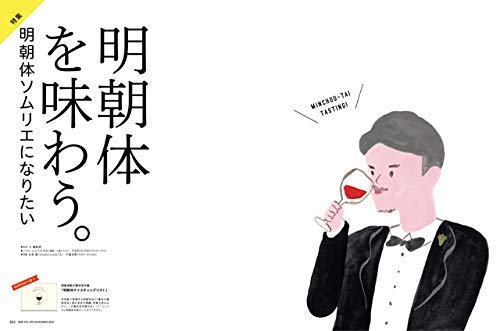
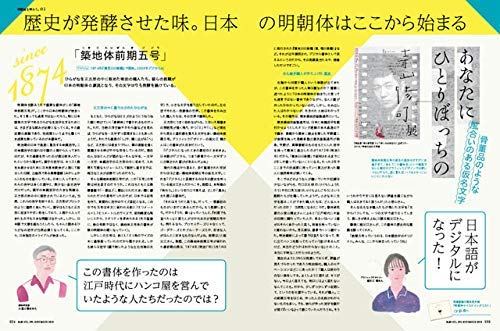
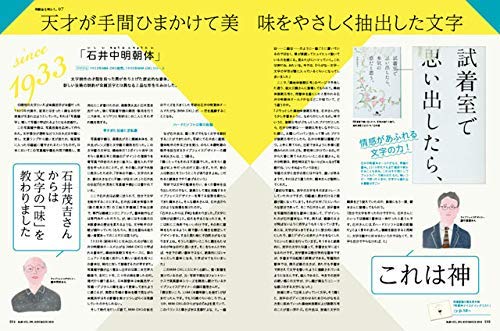
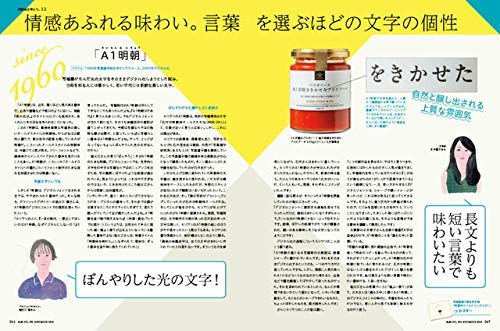
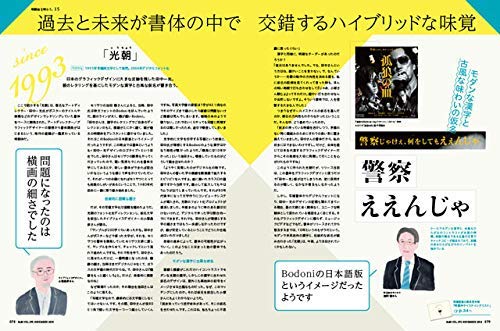
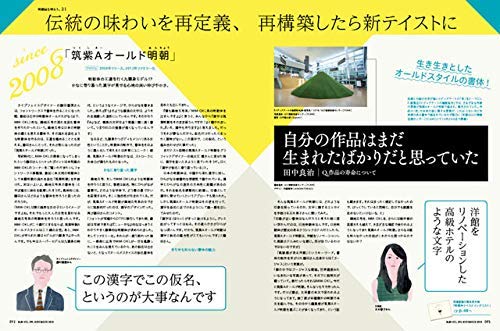
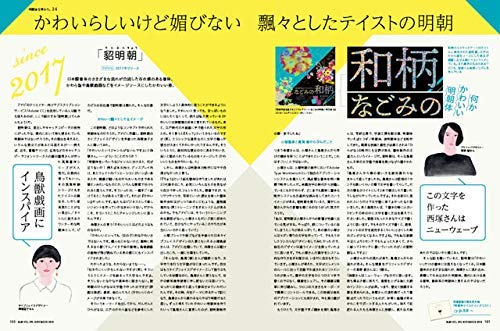
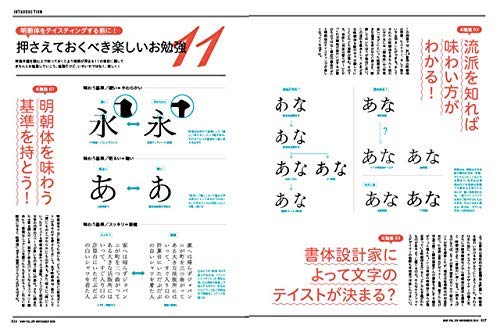
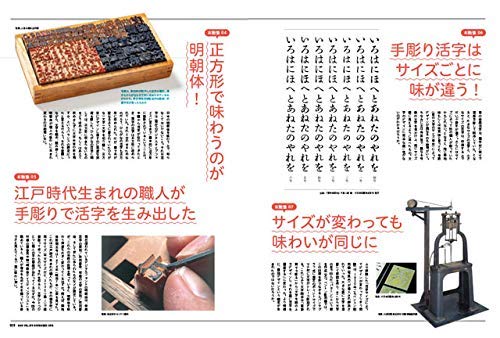
特別付録「明朝体テイスティングリスト」
特別付録「明朝体テイスティングリスト」は、特集に連動した書体見本帳。本誌の特集に登場した27の明朝体の書体見本と組み見本、また味わいを紹介する文章が掲載されている。